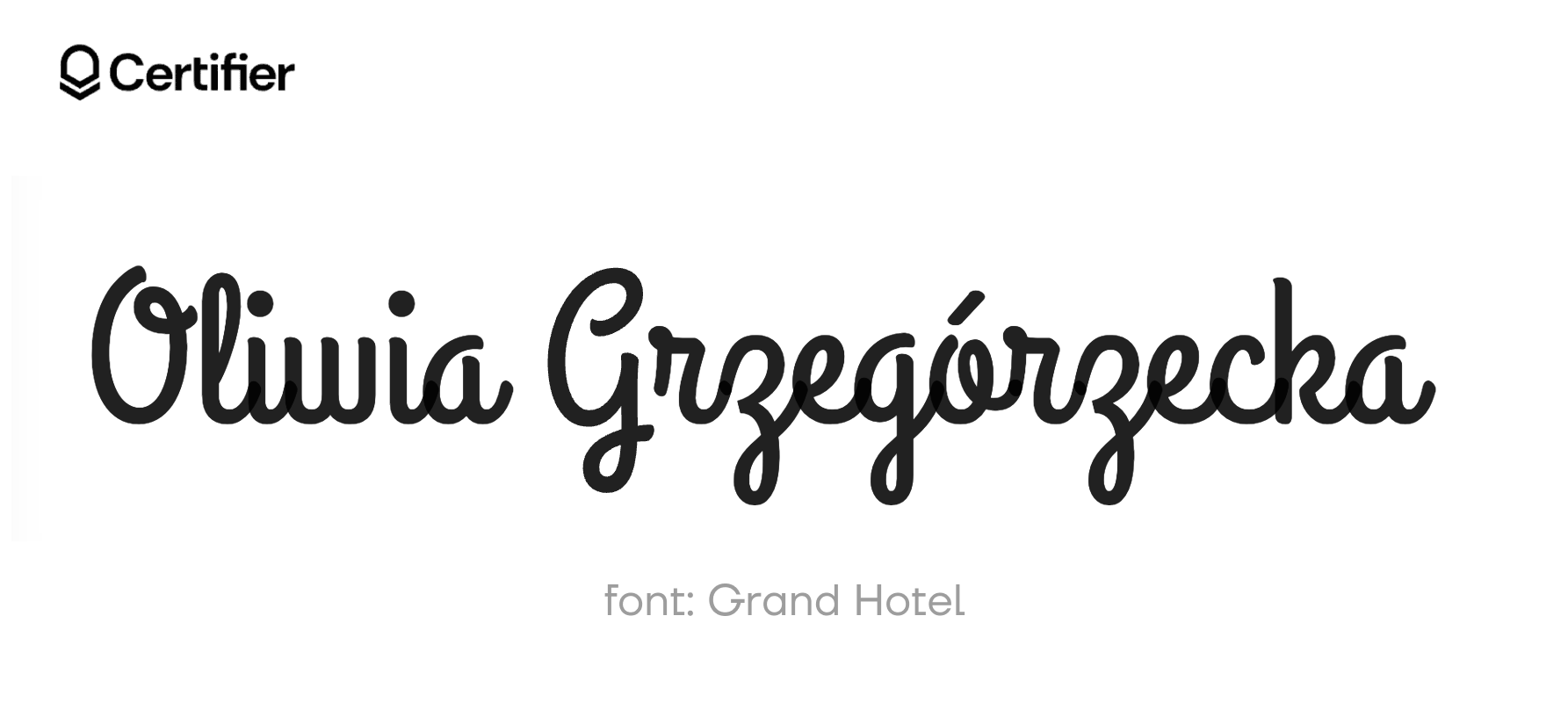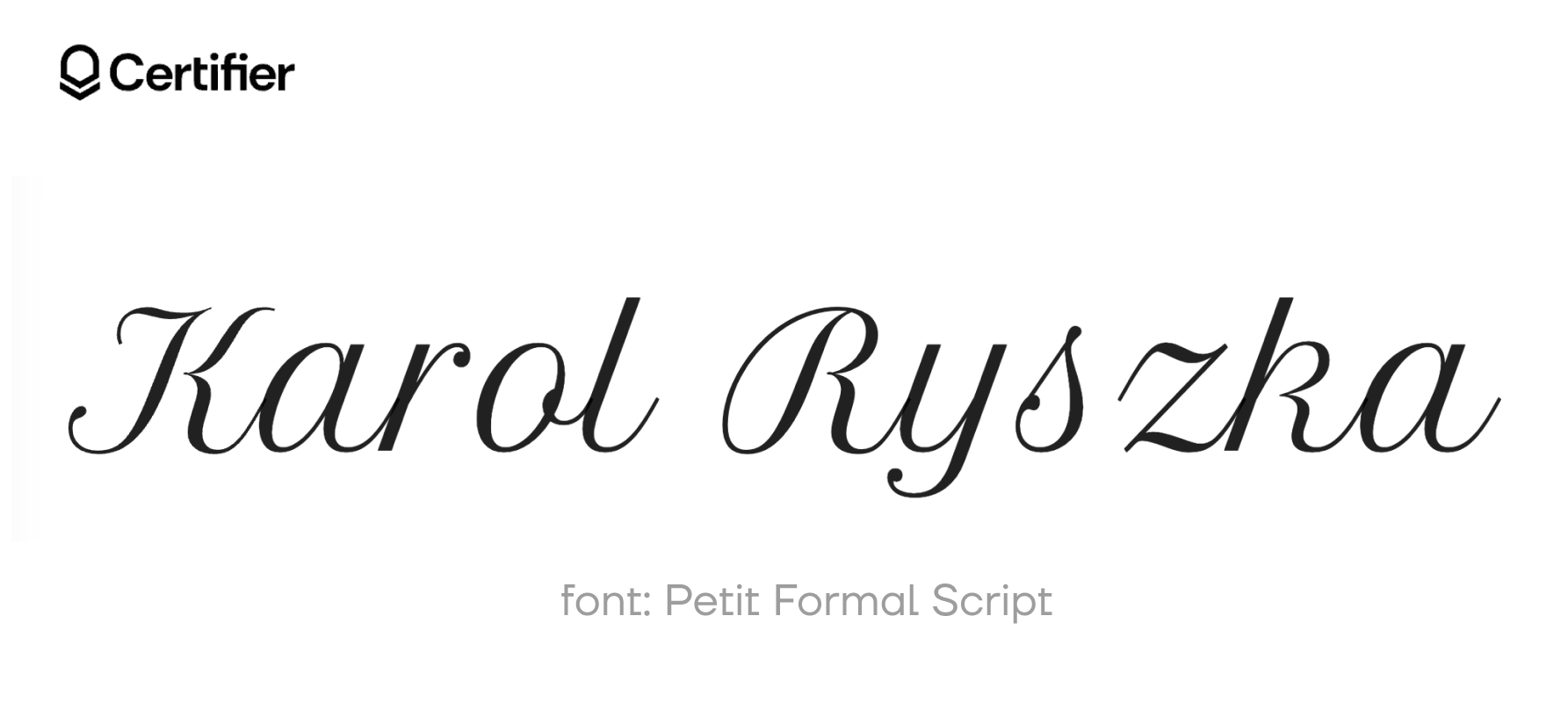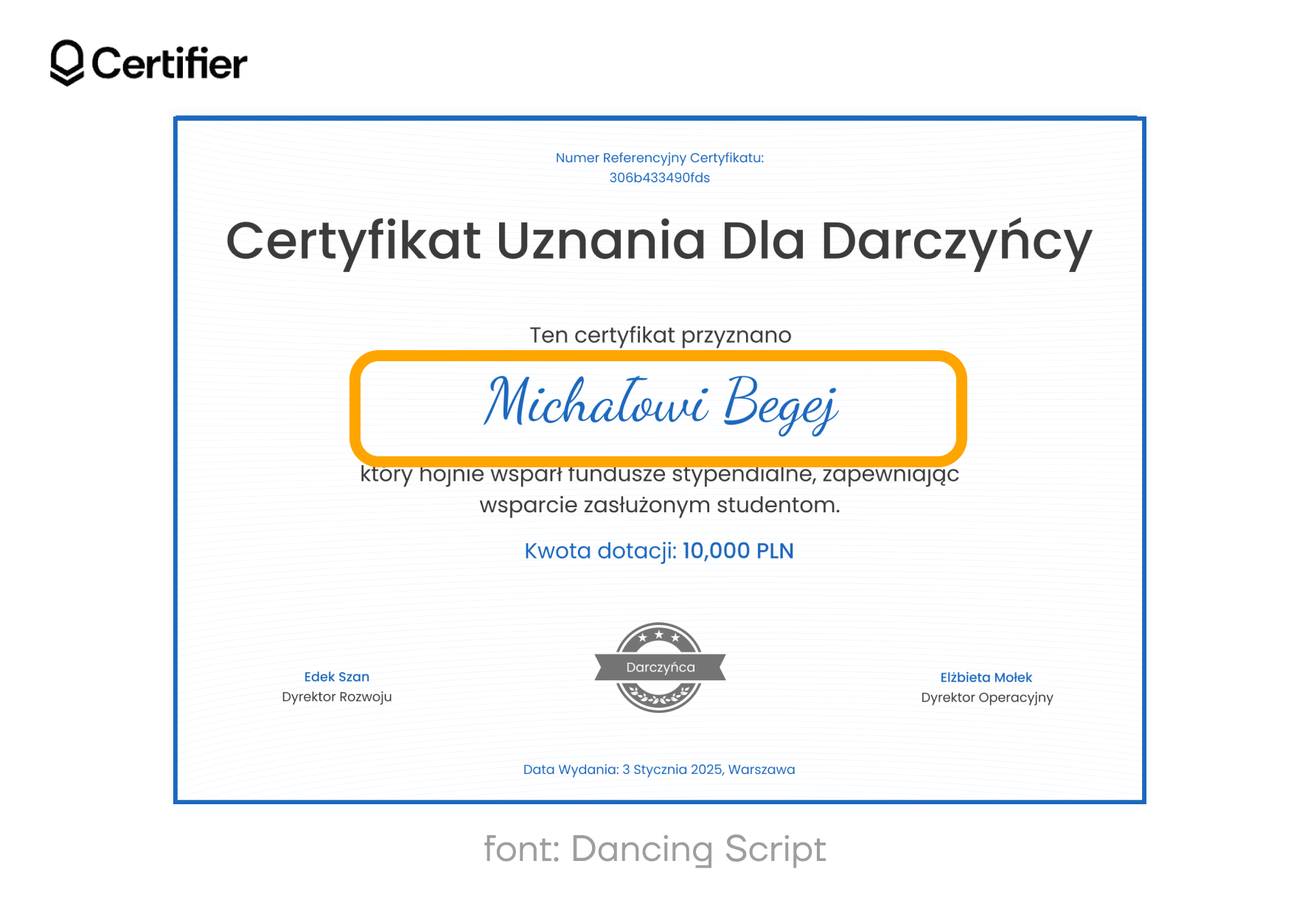
Czcionki odręczne: 30 darmowych czcionek podpisu
W Google Fonts dostępnych jest wiele czcionek, które mogą posłużyć jako podpisy. Nie wszystkie jednak sprawdzają się równie dobrze. Po co tracić czas na szukanie, skoro możesz skorzystać z gotowej listy najlepszych czcionek pisma odręcznego? Czytaj dalej (mała podpowiedź: wszystkie są darmowe!).
Nie musisz używać narzędzia do podpisów, aby podpisać dokumenty online. Wystarczy znaleźć najlepsze czcionki podpisu w darmowym zbiorze jak Google Fonts, aby załatwić sprawę.
Opcje czcionek podpisu są niemal nieograniczone. Gotowy na odkrycie darmowych?
🎨 Przygotowaliśmy tę listę konkretnych fontów wspólnie z naszymi projektantami, którzy regularnie używają ich w naszych szablonach certyfikatów.
Lista darmowych czcionek odręcznych (z polskimi znakami)
Poniżej znajdziesz 30 najlepszych czcionek podpisu, które możesz używać za darmo, bez potrzeby korzystania z generatorów podpisów. Dołączyliśmy szczegółowe opisy oraz podgląd czcionek, aby pomóc Ci wybrać idealną czcionkę podpisu w Dokumentach Google, Word czy Certifier.
01 Alex Brush: Najczęściej używana czcionka podpisu w Google Docs
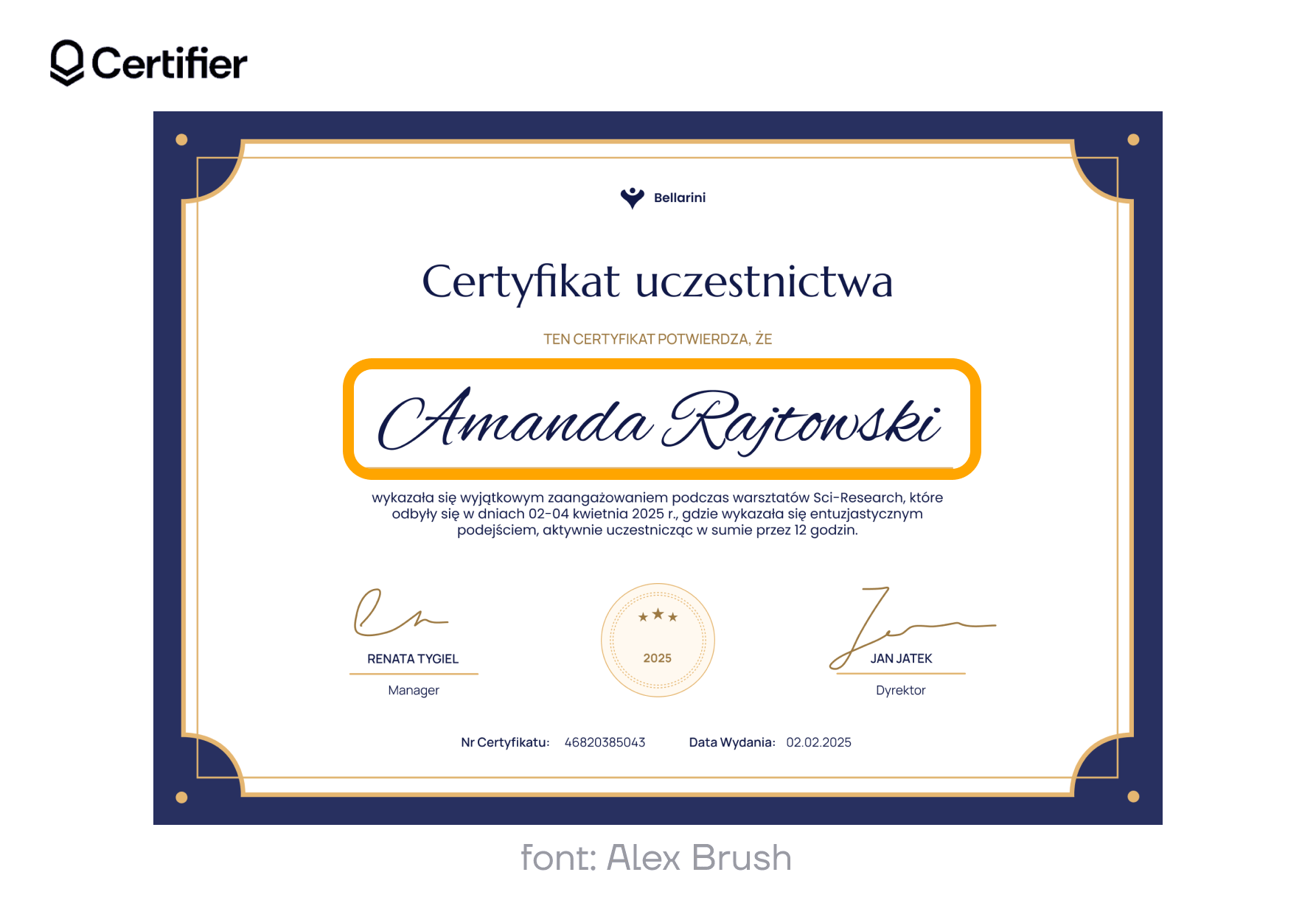
Alex Brush wyróżnia się naturalnym urokiem, który sprawia, że jest idealnym wyborem do wielu dokumentów. Dzięki eleganckiemu stylowi i płynnej, czytelnej kursywie, czcionka ta zwiększa czytelność i dodaje unikalności.
Dlaczego Alex Brush?
Elegancki design
Wszechstronne zastosowanie
Popularny wybór wśród wielu użytkowników
02 Arizonia: Prosta czcionka pismo odręczne
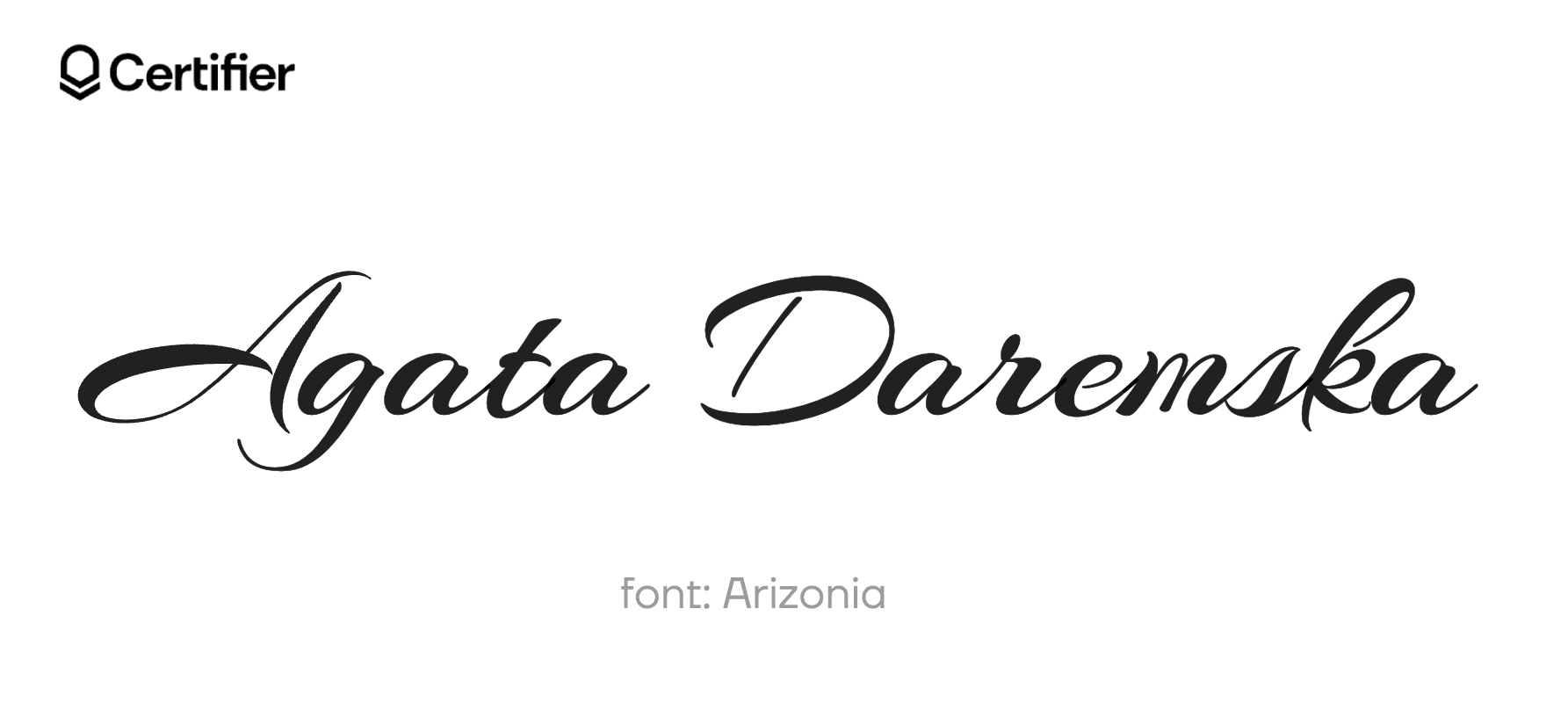
Arizonia charakteryzuje się swobodnym stylem, który potrafi zmienić każdy tekst z nijakiego w piękny bez większego wysiłku. To świetny wybór zarówno do nagłówków na blogu, jak i szczerych notatek z podziękowaniami. Jej wyjątkowość polega na tym, że nadaje słowom osobistego charakteru.
Dlaczego Arizonia?
Eleganckie linie przyciągające uwagę
Sprawdza się w każdym rodzaju dokumentu
Wyrazista, ale stylowa
03 Bad Script: Czcionka idealna do podpisu w Google Docs
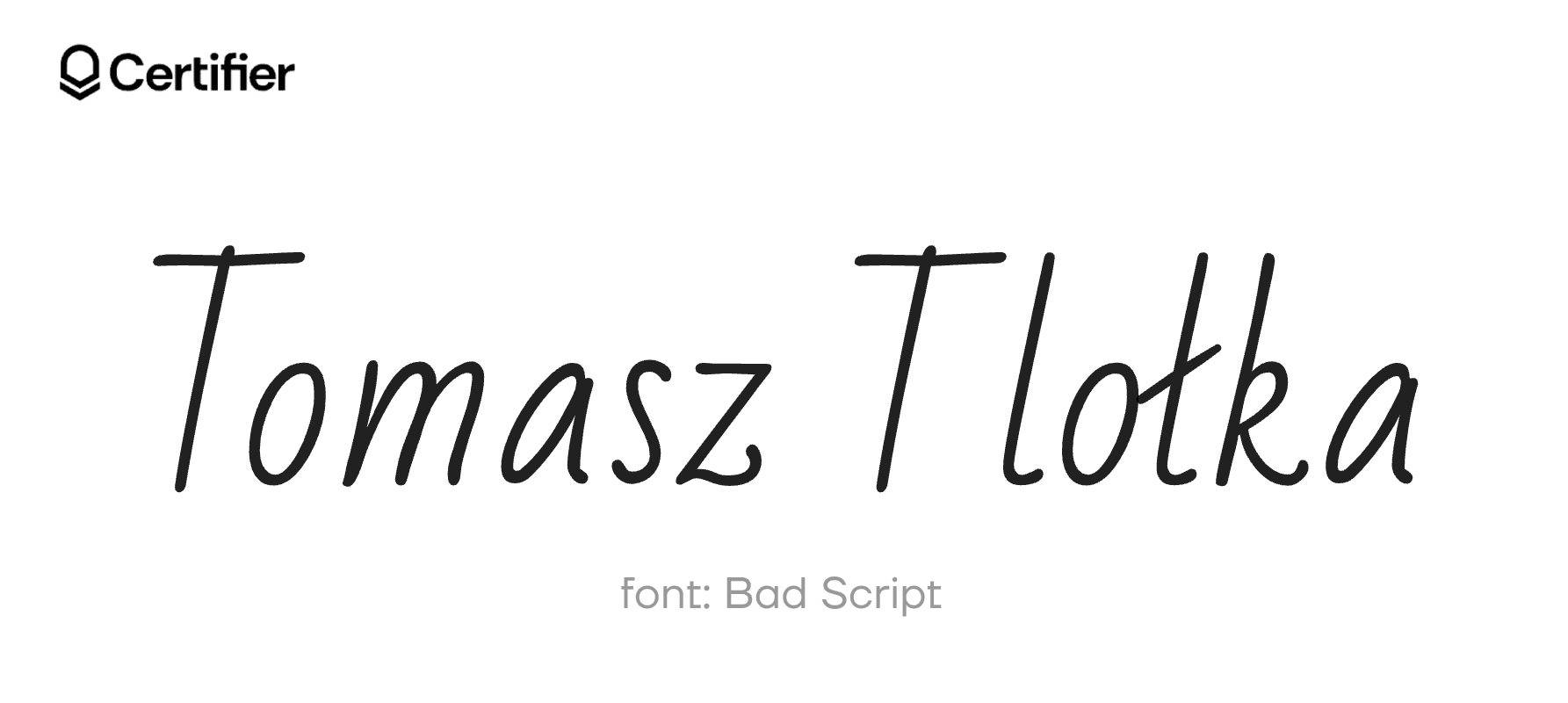
Bad Script przypomina tego znajomego, który wszystko robi z lekkością i swobodą. Świetnie nadaje się, gdy chcesz dodać ludzki akcent, sprawiając wrażenie, że każde słowo zostało starannie zapisane przez Ciebie. Idealna do luźnych notatek lub kreatywnych projektów, gdzie kluczowa jest osobowość.
Dlaczego Bad Script?
Sprawia wrażenie, jakbyś pisał odręcznie
Nadaje dokumentom unikalny charakter
Swobodna, a jednocześnie czytelna
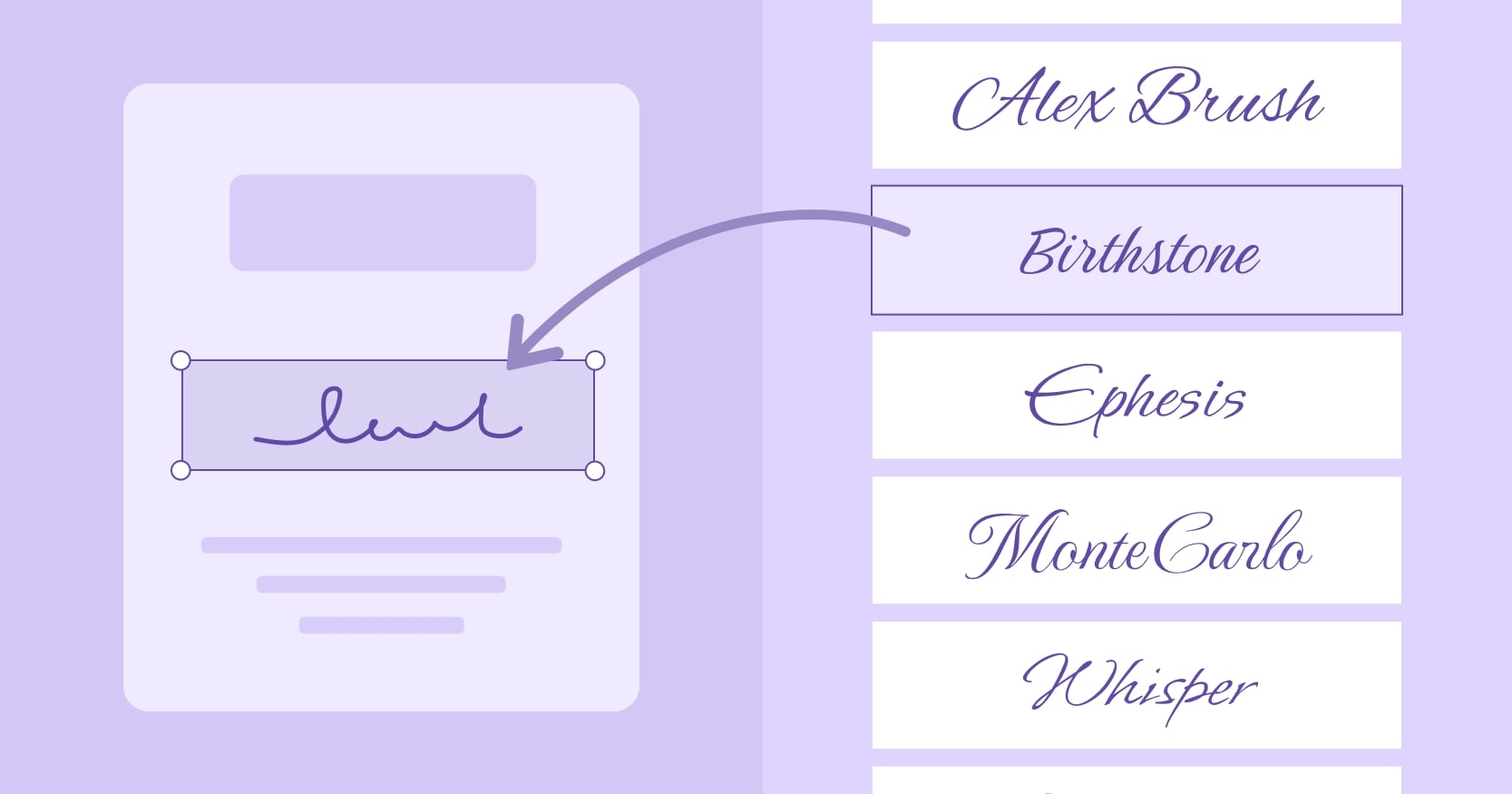
04 Bilbo Swash Caps: Najbardziej futurystyczna czcionka pisma odręcznego
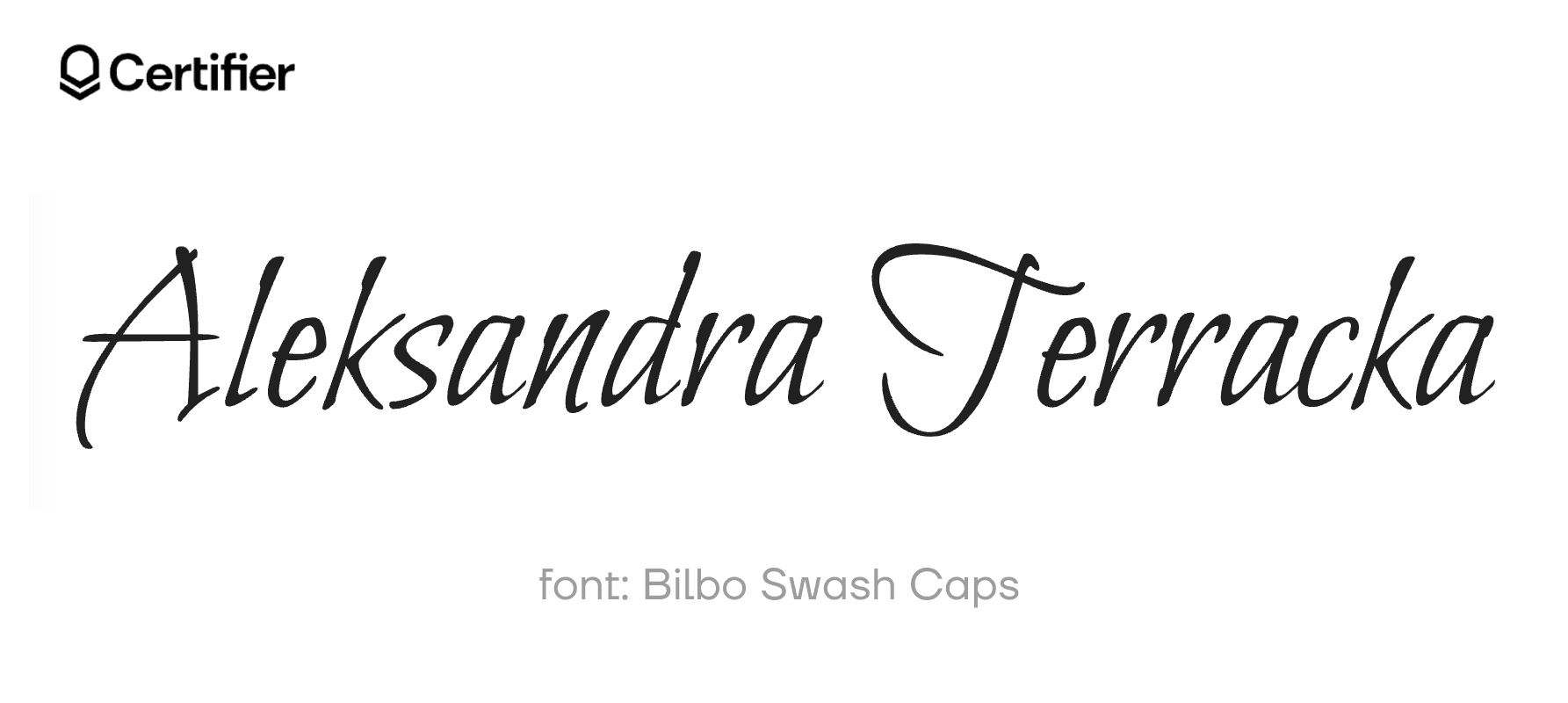
Bilbo Swash Caps to przepustka do świata fantazji. Dzięki śmiałym zdobieniom ta czcionka jest doskonała dla każdego, kto chce dodać odrobinę kreatywności do certyfikatów lub urozmaicić książkę z opowieściami. Każde słowo staje się zaproszeniem do dalszej wyobraźni.
Dlaczego Bilbo Swash Caps?
Zostawia trwałe wrażenie
Kreatywna i wszechstronna
05 Birthstone: Najlepsza rodzina fontów w stylu odręcznym
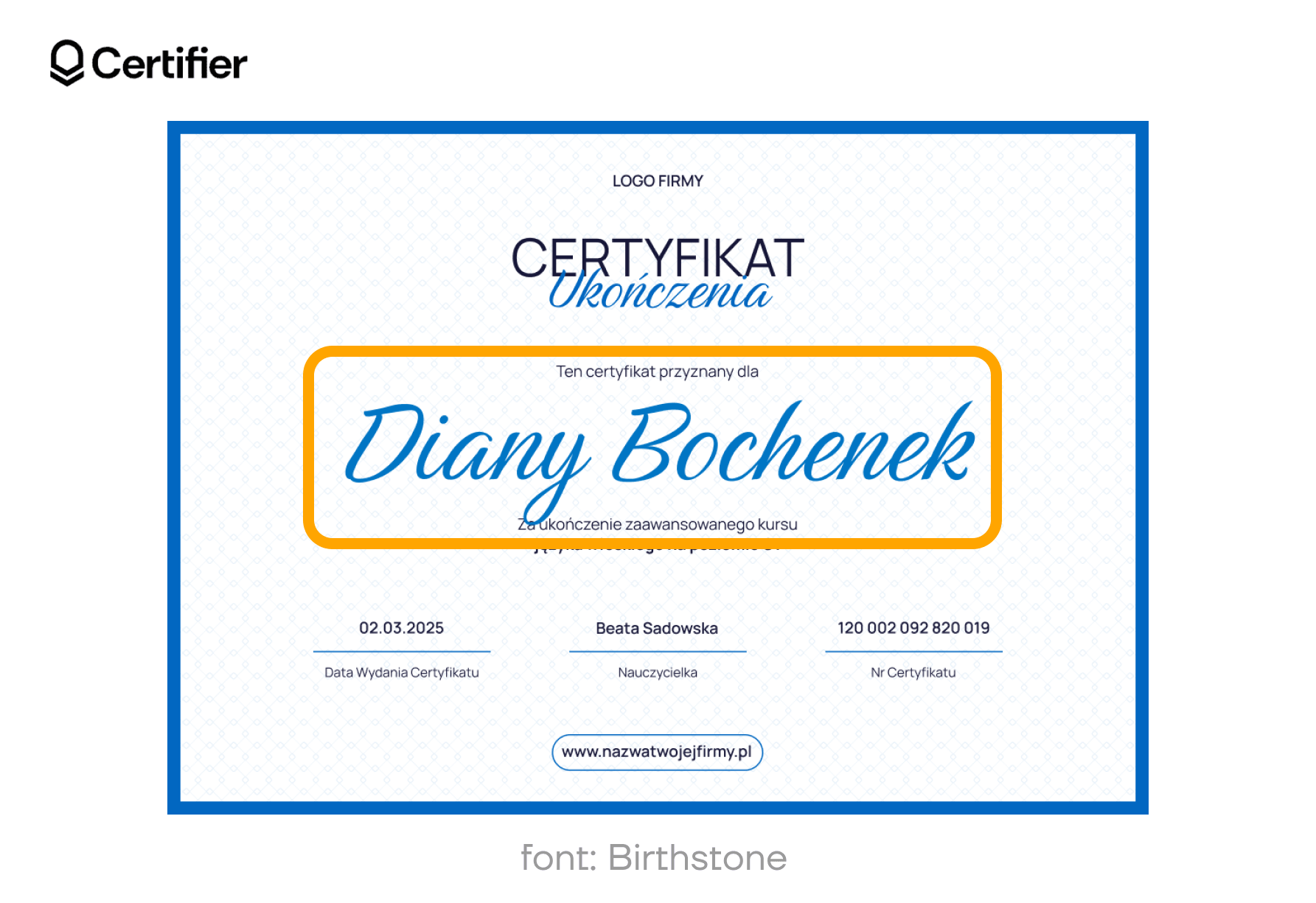
Gdyby fonty były klejnotami, Birthstone byłby diamentem. To font jak ręczne pismo – elegancki, stylowy, i błyszczący na formalnych zaproszeniach czy w projektach reklamowych dla marek premium. Jego wyrafinowane linie sprawiają, że każde słowo wygląda na starannie zaprojektowane i nadaje charakteru projektom o wysokim standardzie.
Birthstone, będący częścią darmowych fontów z open font license, doskonale sprawdza się zarówno w mediach społecznościowych, jak i projektach graficznych. To klasyczne pismo w nowoczesnym wydaniu, które pasuje do fontów szeryfowych i ozdobnych, wzbogacając różne rodzaje fontów w Word czy na Google Docs.
Dlaczego Birthstone?
Ozdabia dokumenty eleganckim pismem odręcznym
Zamienia treści w projekty premium, idealne do użytku komercyjnego
Gwarantuje przejrzysty i wyraźny tekst – nawet z polskimi znakami
06 Allura: Unikalna czcionka jak pismo odręczne
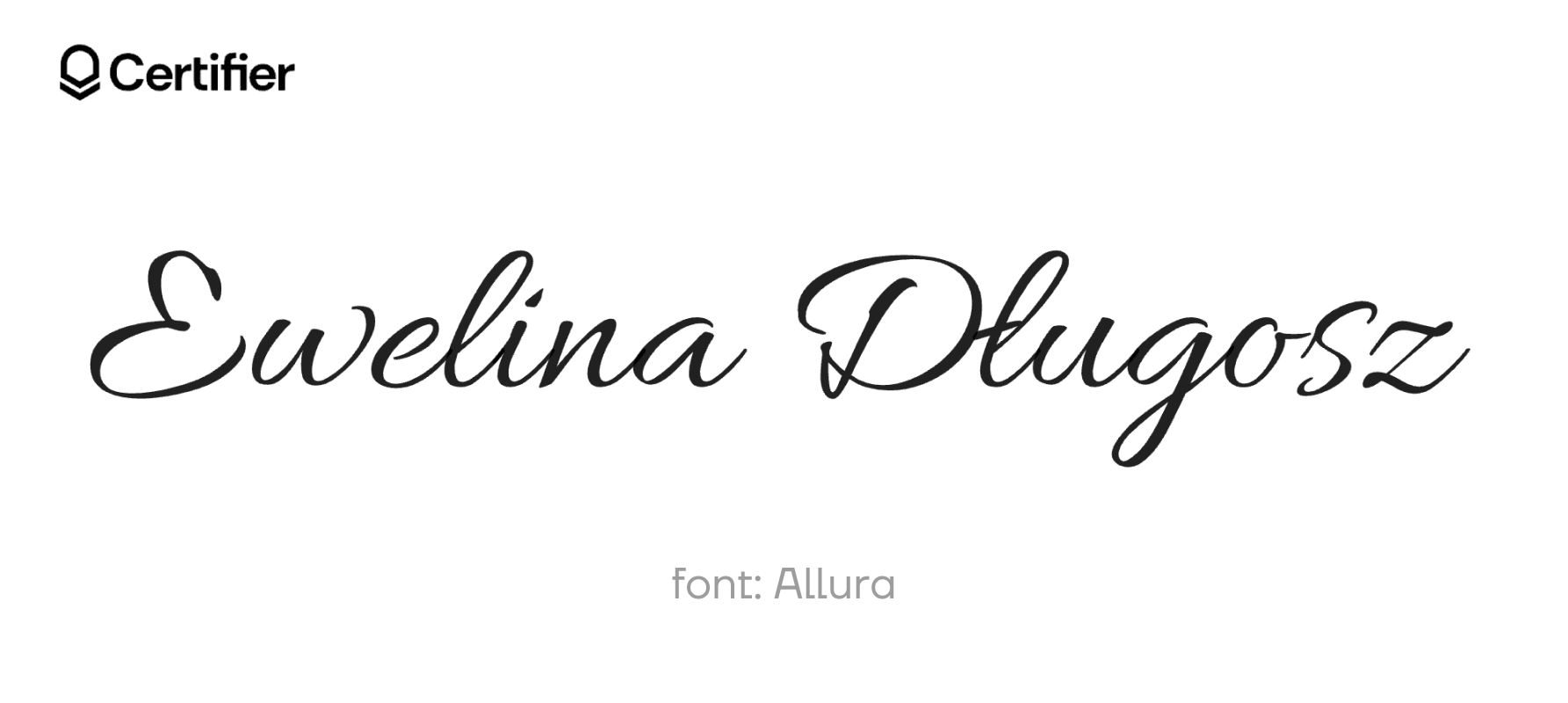
Allura to coś więcej niż zwykły font jak ręczne pismo. Łączy grację kaligrafii z odwagą graffiti – idealny, gdy chcesz, by Twoje słowa ożyły i dosłownie wyskoczyły ze strony. Dodaj eleganckie pismo odręczne do swoich projektów, podkreśl ozdobne pismo odręczne na dyplomach lub użyj go, by Twoja czcionka pisana nabrała charakteru.